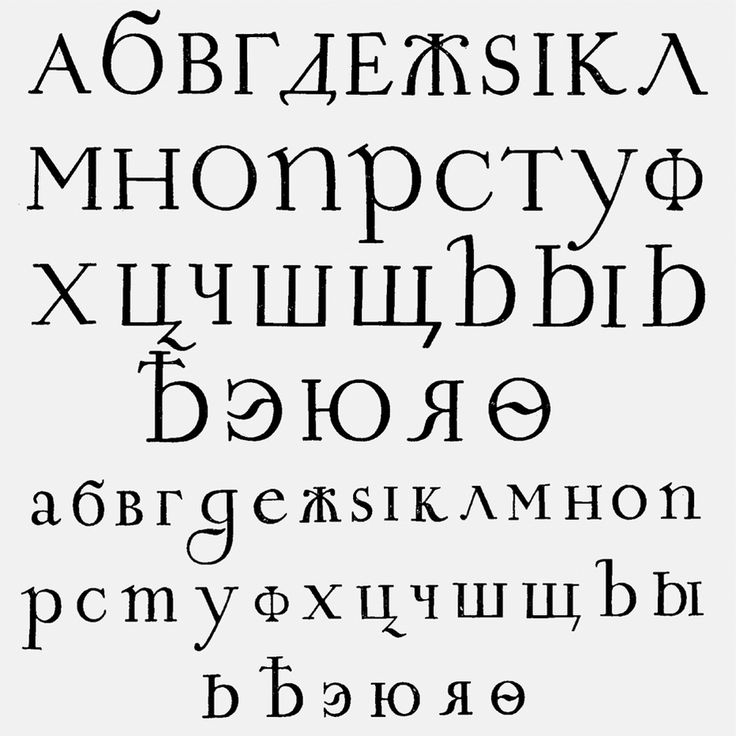
10 новых шрифтов с кириллицей
Собрали для вас свежие шрифты с кириллицей, которые вы сможете использовать, если уже устали от стандартной гельветики.
Стильная дружелюбная антиква с кириллицей, мягкими очертаниями и приятным винтажным характером.
Доступно 6 вариантов насыщенности от Thin до Heavy, а также курсивные версии. Идеально подойдёт для оформления упаковок или брендинга.
Мягкий округлый скрипт с жирными штрихами, обратным наклоном и альтернативными символами. Подойдёт для брендинга, плакатов или оформления упаковки.
Шрифт является дебютной шрифтовой работой Дениса Башева, которую он выполнил при поддержке CSTM Fonts.
Выразительная контрастная антиква с острыми засечками и мягкими овальными штрихами. Шрифт обладает хорошей читабельностью и вобрал в себя лучшие качества традиционных и современных антикв.
Доступны две версии насыщенности, а также курсивные версии.
Уникальная декоративная брусковая антиква с кириллицей, асимметричной формой засечек и стилизацией под украинское народное творчество.
Шрифт разработан в период с 1964 по 1967 год и был предназначен для литья по металлу. Оцифрованная версия содержит латинские и кириллические символы, а также несколько орнаментов.
Доступно два варианта насыщенности и наклонные версии. Идеально подойдёт для проектов о традиционном восточноевропейском творчестве.
Современный гротеск с кириллицей, низким контрастом и геометричной формой знаков.
Доступно 6 вариантов насыщенности и наклонные версии. Подойдёт для брендинга, оформления упаковки, набора текста и других задач.
Нежный жизнерадостный скрипт с кириллицей и компактной формой знаков.
Содержит полный набор прописных и строчных символов.
Отлично подойдёт для брендинга, свадебных приглашений, дизайна меню и многого другого.
Функциональный сбалансированный гротеск с кириллицей и набором пиктограмм обзавёлся курсивом. Теперь доступно 6 прямых и 6 курсивных начертаний от Thin до Black.
Шрифт может похвастаться высокой читабельностью и разработан специально для оформления навигации. Также отлично подойдёт для брендинга, упаковки или набора текста.
Дружелюбный вариативный гротеск с кириллицей и низким контрастом. Семейство содержит дополнительные версии с поддержкой арабского и греческого языка и предназначено для распространения на глобальном рынке.
В каждой версии доступно по 8 статичных начертаний от Thin до Black.
Вариативный гуманистический гротеск с кириллицей, высоким контрастом и элегантными расклёшенными засечками.
Шрифт прекрасно подойдёт для брендинга, оформления упаковки или плакатов.
Стильный вариативный полуоткрытый гротеск с кириллицей для широкого спектра задач. Подойдёт как для заголовков, так и для набора.
Содержит 6 вариантов ширины от Compact до UltraExtended, и большую градацию по весу от от Thin до Black. Для покупки доступно 30 статичных и 12 вариативных версий на выбор.